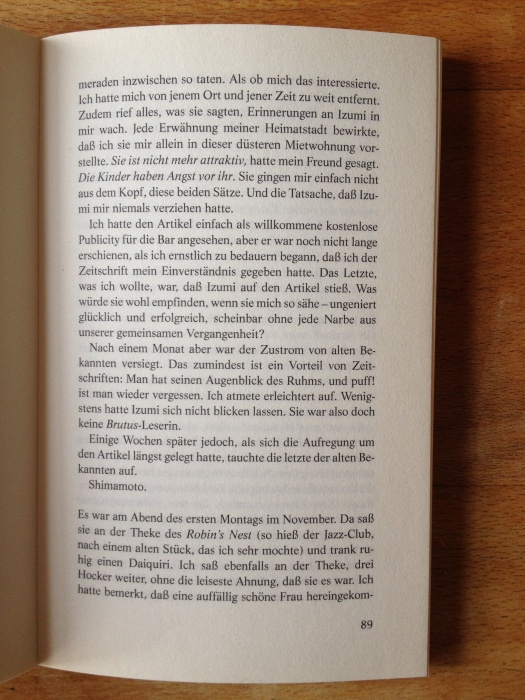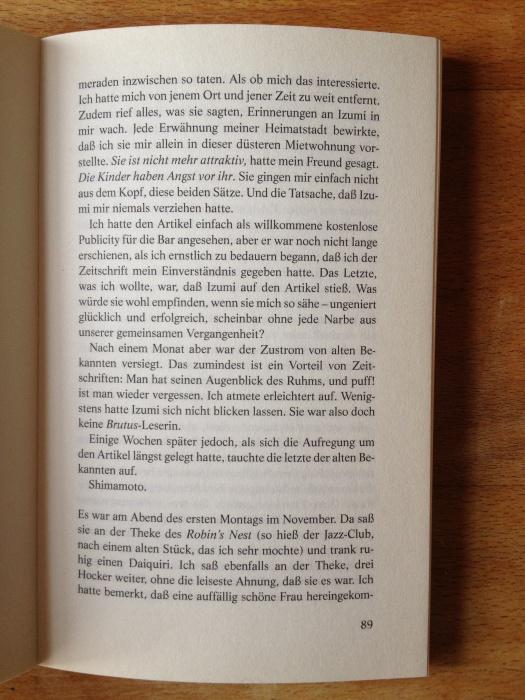
Wie nennt man das "Halte inne!" in Form von vertikalem Extra-Abstand zwischen Absätzen in Büchern?
Ein Szenen- oder Perspektivwechsel oder das Überspringen eines kleinen Zeitraums, was jedoch kein neues Kapitel rechtfertigt, wird in vielen Büchern mit einem vertikalen Extra-Abstand vermittelt.
Der sperrige Thementitel zeigt Euch, dass mir weder Jargon noch Geschichte dieses Mittels bekannt sind.
Mein Empfinden der Botschaft ist: "Halte kurz inne im Lesefluss!".
Vielleicht empfindet ihr das abwegig und deutlich anders?
Ich kenne viele Bücher, aber keinen vertikalen Extra-Abstand. Kannst du ein Beispiel zeigen?
Ein Bild hängt an.
Haruki Murakami. Gefährliche Geliebte. Seite 89.
Ich denke er meint die Leerzeile vor dem letzen Absatz „Es war am Abend des …“ ich wüsste aber nicht, dass das nen Namen hat – bei LaTeX bspw. ist dass schlicht ein \bigskip.
Richtig, ich meine die Leerzeile vor "Es war ein Abend ...".
Da die Leerzeile eine spezifische Bedeutung hat, dachte ich, es gäbe dafür einen Fachbegriff, der genau diese Bedeutung transportiert.
Nach einigen wahllosen Griffen ins Regal gibt's das nicht in allen, aber in vielen Büchern.
Die meisten verzichten dann nach der Leerzeile auf den Einzug der ersten Zeile, also ist es wohl mit einem \bigskip alleine nicht getan (ohne das jetzt probiert zu haben)?
Stimmt, man brauch (\par)\bigskip\noindent* – aber da hier eh kaum jemand LaTeX kennt und was darüber wissen will, dachte ich, es reicht zur Namensfindung der \bigskip ;-)
Vielleicht hilft es bei der Suche nach Bezeichnungen: Es gibt doch auch die Möglichkeit in den Abstand drei Sterne oder nen Aldusblatt zu setzten, gibt’s dafür nen Namen?
* Dafür sollte man dann nen eigenen Befehl bauen, z.B. \newcommand{\bigpar}{\par\bigskip\noindent\ignorespaces} …
In den meisten Büchern von Pratchett sind besagte Leerzeilen die höchste Form der Unterteilung (Kapitel u. Ä. gibt es nicht). Drei Sterne werden genutzt um derartige Umbrücke zu kennzeichnen, die auf einen Seitenumbruch fallen.
»Leerzeile« halt. ;-)
ich lernte das damals im bleisatz als blindzeile kennen.
Blindzeile ist der Fachausdruck für jede Leerzeile zwischen zwei Absätzen, egal wie groß (Drittel, halb, usw.), und auch wenn der Gesamttext teils oder ausschließlich mittels Blindzeilen strukturiert wird. Eine besondere Bedeutung, wie sie Ibu meint, hat die Blindzeile aber nicht.